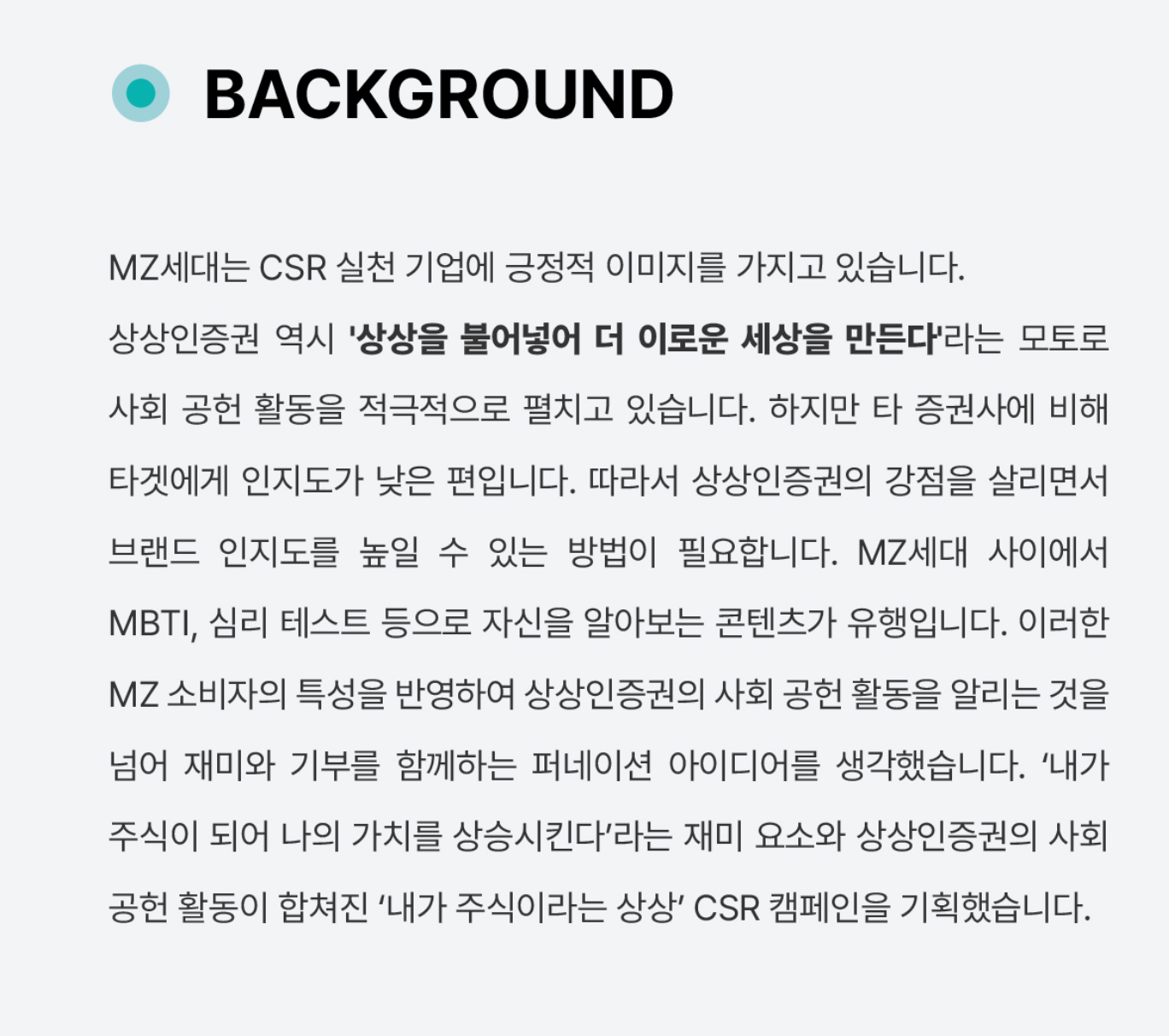
어떤 폰트인지 궁금합니다! yeo*** 2023.07.10 아래 이미지 댓글 0 등록 오타대마왕 노토산스나 프리텐다드 같은데 구둣점을 보니 프리텐다드 같아요. 2023-07-10 답글 달기 댓글 더보기 쉽고 빠르게 가장 비슷한 폰트를 알고 싶다면? 이미지로 검색하기
노토산스나 프리텐다드 같은데 구둣점을 보니 프리텐다드 같아요.